意外と多い仮名系グリフ02「濁点・半濁点つき、小書き」
シリーズ前回の記事はグリフ数の話でしたが、今回は作るポイントの紹介です。
濁点・半濁点つきの仮名
元の字にそのまま濁点・半濁点を付け足すだけで上手くいくとは限りません。点がついても元の字と同じくらいの黒味に見えるよう文字全体を少し小さくしたり、点と筆画がかぶってしまわないよう一部を短くしたり、それぞれの文字に合わせて調整します。
元の文字の調整とは別に、濁点・半濁点の配置や大きさも文字ごとに調整します。文字を組んだときにはだいたい同じような濁点・半濁点に見えるようにするのもポイントです。
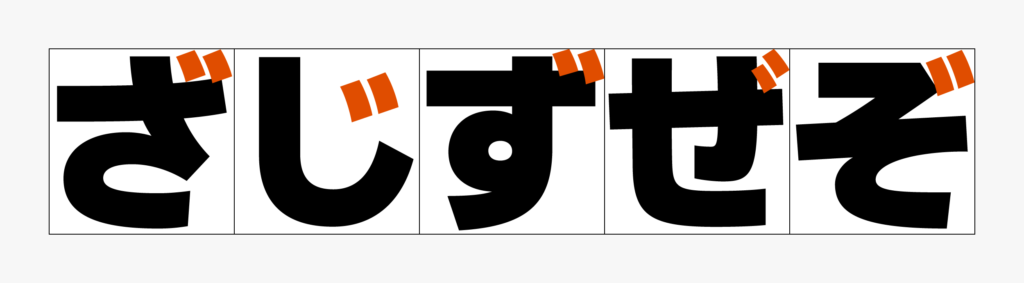
小書きの仮名
縮小しただけだと線が細くなってしまうので、太くするまでがセットです。組んだ時に他の文字と黒味が揃うようしつつ、縮小で狭くなってしまった部分などがあれば合わせて調整します。実際に制作する際は状況にもよりますが、元の字を少し太いウエイトで出力、縮小、調整、という手順で作っています。
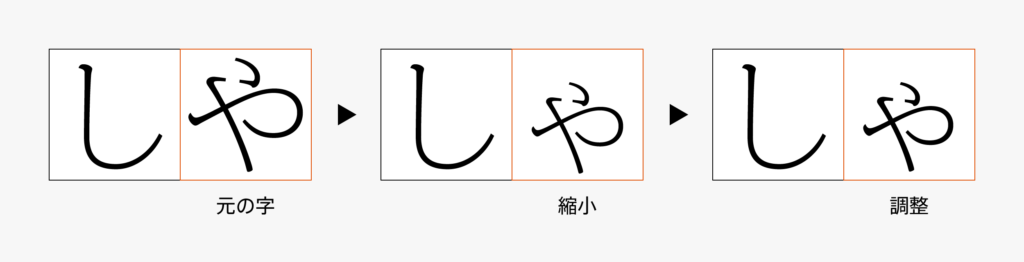
小書きの仮名は縦組み用と横組み用をそれぞれ用意することも忘れずに。